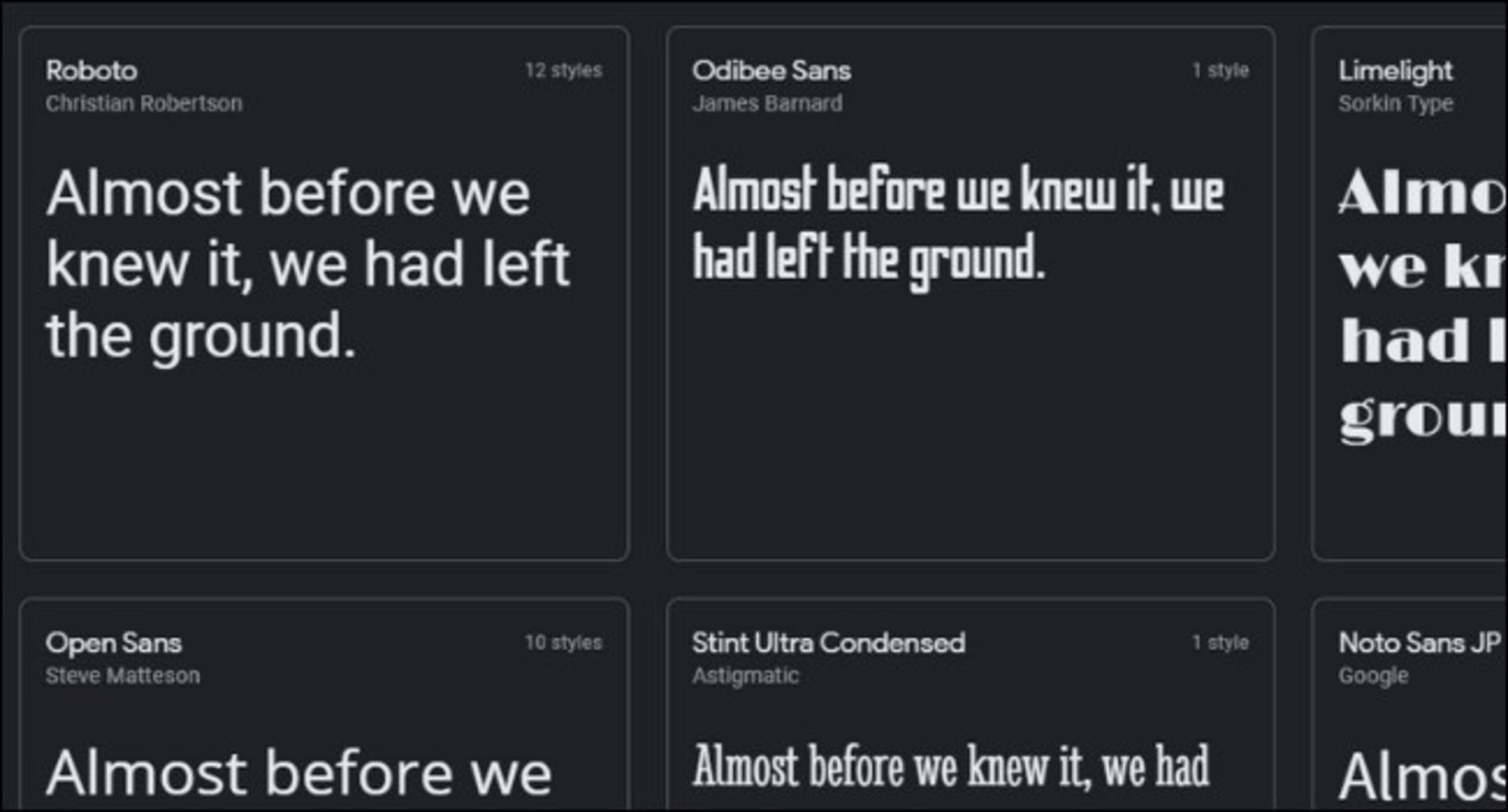
وب فونت چیست و چگونه کار می‌کند؟
آیا می‌دانید مرورگر وب شما به‌طور خودکار از فونت‌هایی که روی سیستم‌تان نصب شده، استفاده می‌کند؟ فونت‌های وب، به صفحاتی که هر روز آن‌ها را مرور می‌کنید کمک می‌کند تا بهتر دیده شوند. اما وب‌فونت (WebFont) چیست و چگونه کار می‌کند؟
همه‌ی ما هر روز از فونت استفاده می‌کنیم. برخی از فونت‌ها به‌همراه سیستم‌عامل ارائه می‌شوند. پس از نصب برخی از برنامه‌ها مثل Adobe Creative Suite یا مایکروسافت آفیس، می‌توانید از فونت‌های نصب‌شده روی سیستم خود در این نرم‌افزارها استفاده کنید. این نوع فونت‌ها به‌صورت محلی روی حافظه‌ی سیستم شما ذخیره می‌شوند که به آن‌ها فونت دسکتاپ نیز گفته می‌شود.
اما با تغییر تجربه‌ی کار با رایانه‌ها در فضای آنلاین، نوع دیگری از فونت‌ها اهمیت پیدا کرده است. «وب‌فونت» در واقع فونتی است که روی فضای ابری ذخیره می‌شود و برای تولید متنی که در وب‌سایت‌ها نمایش داده می‌شود (مثل متن همین مقاله)، مورد استفاده قرار می‌گیرد.
تاریخچه مختصری از فونت‌وب
به گزارش HowToGeek، در روزهای اولیه‌ی اینترنت، تایپوگرافی در صفحات وب به فونت‌هایی محدود بود که روی سیستم کاربر نصب شده بود. بدین ترتیب اگر فونتی روی سیستم نصب نبود، وب‌سایت‌ها از یک فونت استاندارد بهره می‌بردند که احتمال نصب بودن آن روی سیستم وجود داشت. به‌همین دلیل طراحان وب اغلب از فونت‌های سیستمی پیش‌فرش در سایت‌های خود استفاده می‌کردند.
مایکروسافت مجموعه‌ای از فونت‌ها را به‌طور رایگان برای طراحی وب در دسترس قرار داده است. این بسته شامل فونت‌های سیستمی پرکاربرد مثل Comic Sans، Arial، Times New Roman و Trebucket بود. از طرف دیگر، طراحان می‌توانند از خانواده‌ی فونت‌هایی مثل Sans-Sefif، Serif و Monospace برای تعیین سبک کلی یک فونت بهره ببرند، حتی اگر آن فونت خاص در دسترس نباشد.
گوگل در سال ۲۰۱۰ با معرفی فونت‌های خود، وضعیت را تغییر داد. از آن زمان به‌بعد، رقبای دیگری مثل ادوبی تایپ‌کیت و افزونه‌های فونت میزبان‌وب، در دسترس قرار گرفت. میلیون‌ها وب‌سایت از سراسر جهان با وب‌فونت‌هایی مثل مجموعه‌ی فونت‌های گوگل اجرا می‌شوند.
وب‌فونت چگونه کار می‌کند
بزرگ‌ترین ارائه‌دهنده‌ی وب‌فونت، فونت‌های گوگل بوده که شامل یک کتاب‌خانه‌ی وب گسترده با بیش از هزار فونت است. می‌توان از این فونت‌ها با استفاده از CSS در وب‌سایت‌های مورد نظر بهره گرفت. توسعه‌دهندگان گوشی‌های هوشمند نیست می‌توانند هنگام ساخت اپلیکیشن‌های اندروید، به این فونت‌ها دسترسی داشته باشند.
هنگامی که یک صفحه‌ی وب از فونت‌های گوگل استفاده می‌کند، فونت مورد نظر از پایگاه داده‌ی گوگل دریافت و سپس متن روی مروگر با استفاده از آن فونت به شما نمایش داده می‌شود. این فونت‌ها در سرور گوگل میزبانی می‌شود و تقریبا بلافاصله پس از درخواست، روی دستگاه کاربر بارگیری می‌شود. سایر خدمات فونت‌های ابری نیز تقریبا روش کارکرد مشابهی دارند.
جایگزین دیگر، استفاده از فونت‌های میزیبان و جاسازی شده در وب است. اینکار از طریق WOFF (خلاصه‌ی شده‌ی عبارت Web Open Font Format) انجام می‌شود. پسوند woff، درواقع یک فایل فونت فشرده است که توسط موزیلا توسعه یافته و با اکثر مرورگ‌های مدرن، سازگاری دارد. اگر قصد دارید از یک فونت سفارشی استفاده کنید ولی آن فونت در سرویس‌های وب‌فونت ارائه نشده است، می‌توانید از woff بهره ببرید.
پایگاه فونت‌های گوگل و همه‌ی فونت‌های زیرمجموعه‌ی آن، کاملا رایگان و برای همه‌ی کاربران در دسترس است. این پایگاه فقط از فونت‌های تحت مجوز منبع‌باز استفاده می‌کند و بسیاری از فونت‌ها مثل Lato، Roboto و Montserrat از جمله مهم‌ترین فونت‌هایی محسوب می‌شوند که امروزه در بسیاری از وب‌سایت‌ها مورد استفاده قرار می‌گیرد. گوگل این فونت‌ها را در یک وب‌سایت مخصوص میزبانی می‌کند. شما می‌توانید در این وب‌سایت حتی فونت‌های مختلف را باهم مقایسه کرده و آن‌ها را امتحان کنید. گوگل همچنین پایگاه داده‌ای از نمادهای رایگان در دسترس کاربران قرار داده است.